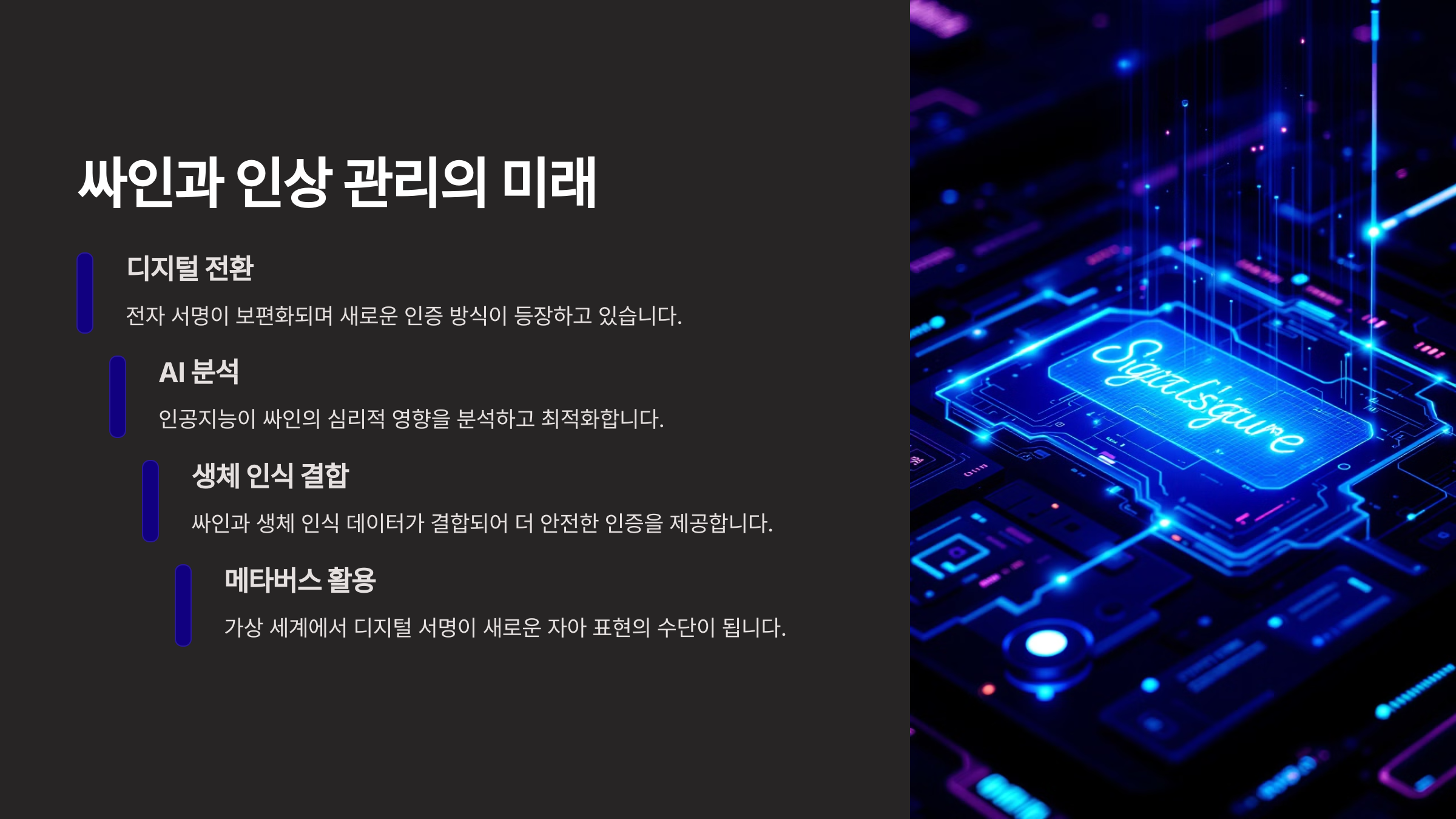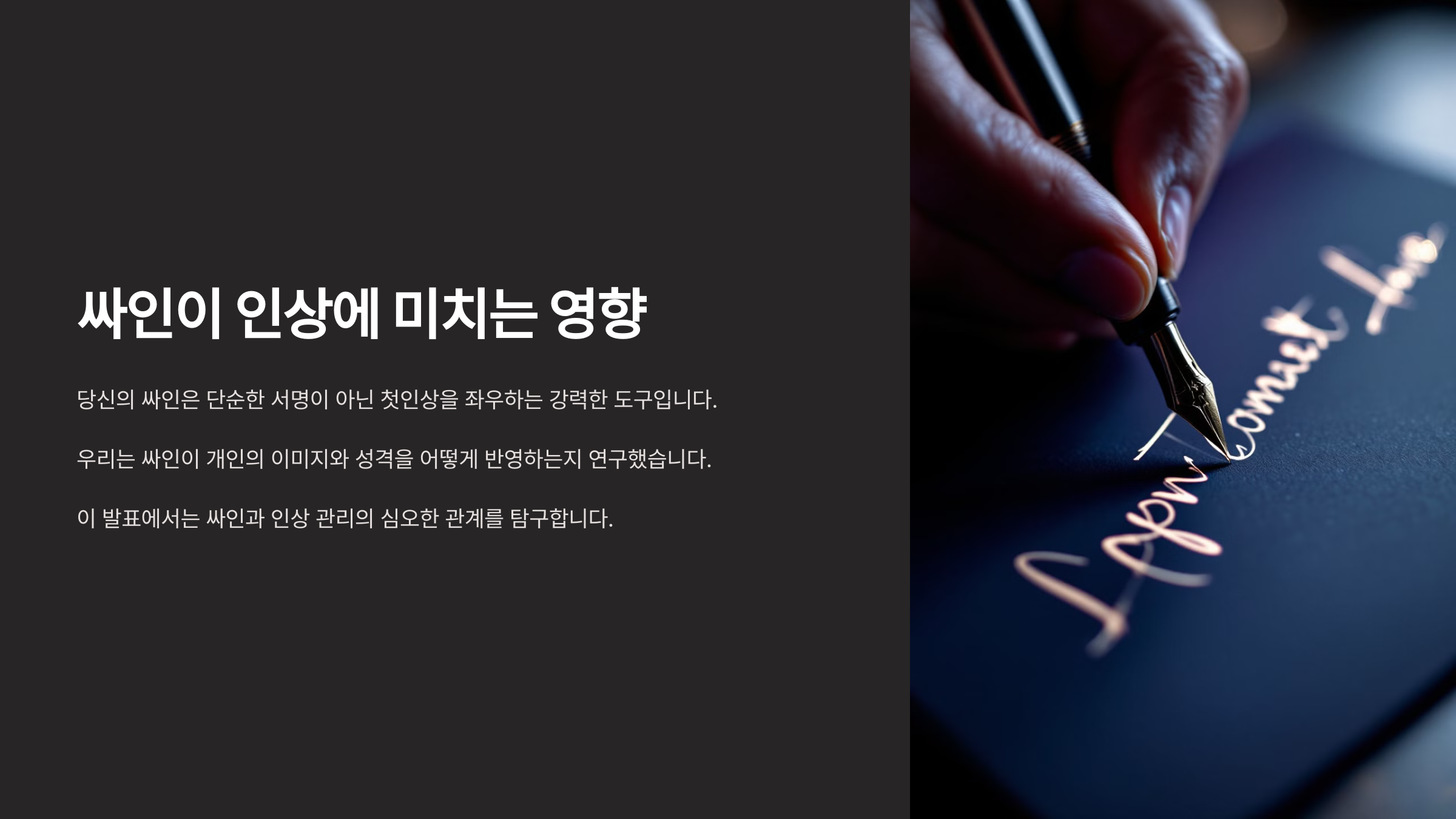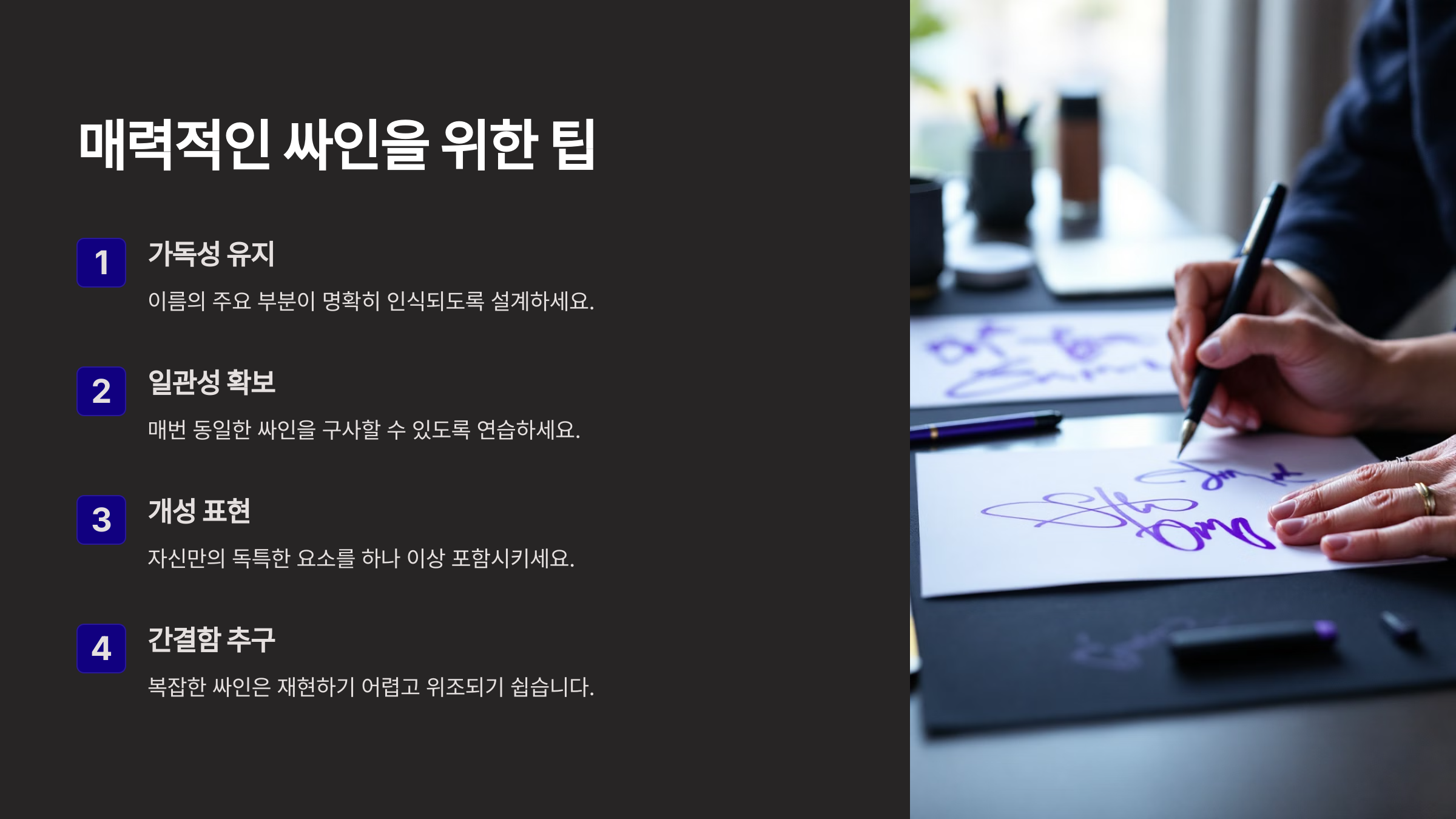
우리는 사람의 인상을 얼굴, 말투, 행동으로 판단하지만, 싸인 하나만으로도 인상이 달라 보일 수 있다는 사실! 알고 계셨나요? 🤔 싸인은 단순한 서명이 아니라 개성과 성향을 담은 또 하나의 얼굴이에요.
그럼 싸인을 바꾸면 어떤 인상 변화가 일어나는지 함께 알아볼까요? 🚀
싸인이 인상에 미치는 영향 👀
싸인은 우리가 의식하지 못하는 사이에 상대방에게 첫인상을 결정짓는 중요한 요소로 작용할 수 있어요. 그렇다면 싸인은 왜 사람의 인상에 영향을 미칠까요? 🤔
📌 싸인이 인상을 좌우하는 3가지 이유
• ✍ 필체의 감정 전달 → 싸인의 필체는 사람의 성향과 감정을 반영해요.
• 🔍 스타일의 상징성 → 싸인의 디자인이 곧 그 사람의 성격을 표현할 수 있어요.
• 💼 전문성과 신뢰감 → 세련된 싸인은 더 신뢰감을 주는 효과가 있어요.
싸인의 모양과 스타일이 달라지면 상대방이 느끼는 이미지도 달라질 수 있어요. 그럼 싸인의 심리학적 의미도 함께 살펴볼까요? 😆
싸인의 심리학적 의미 🧠
싸인은 단순한 글씨가 아니라 개성과 심리를 반영하는 요소예요. 어떤 스타일의 싸인을 사용하는지에 따라 그 사람의 성향과 성격이 드러날 수 있죠. 그렇다면 싸인의 형태별로 어떤 심리적 의미를 담고 있는지 살펴볼까요? 🤔
📌 싸인 스타일별 심리적 의미
싸인 스타일 심리적 의미
크고 화려한 싸인 자신감이 높고 외향적인 성격
작고 단순한 싸인 신중하고 내성적인 성격
곡선이 많은 싸인 감성적이고 창의적인 성향
직선 위주의 싸인 논리적이고 강한 리더십
기울어진 싸인 역동적이고 에너지가 넘치는 성격
이처럼 싸인의 디자인만 보고도 어느 정도 성향을 유추할 수 있어요. 그럼 싸인의 스타일별로 인상이 어떻게 변하는지도 알아볼까요? 🔍
싸인 스타일별 인상 변화 🔄
싸인의 스타일을 바꾸면 상대방이 받는 인상이 달라질 수 있어요. 같은 이름이라도 어떤 디자인을 적용하느냐에 따라 다른 분위기를 연출할 수 있죠! 그럼 스타일별 인상 변화를 비교해볼까요? 😊
📌 싸인 스타일에 따른 인상 변화
싸인 스타일 주는 인상
날렵한 필기체 싸인 스타일리시하고 세련된 느낌
굵은 획의 강한 싸인 신뢰감과 강한 카리스마
곡선이 많은 싸인 부드럽고 친근한 이미지
작고 정돈된 싸인 섬세하고 꼼꼼한 느낌
대각선으로 기울어진 싸인 역동적이고 활동적인 성격
싸인을 조금만 수정해도 전혀 다른 인상을 줄 수 있다는 것! 그럼 싸인을 바꾸기 전과 후의 차이를 비교해볼까요? 🤩
싸인 변경 전후 비교 🔄
싸인을 바꾸기 전과 후를 비교하면 상대방이 느끼는 인상이 어떻게 변하는지 명확히 알 수 있어요. 싸인을 조금만 수정해도 더 전문적이고 세련된 분위기를 연출할 수 있답니다! 🤩
📌 싸인 변경 전후 비교 사례
변경 전 변경 후 인상 변화
작고 삐뚤어진 싸인 균형 잡힌 필기체 싸인 더 정돈되고 신뢰감 있는 인상
단순한 이니셜 싸인 곡선과 기호가 추가된 싸인 더 개성 있고 창의적인 느낌
너무 복잡한 싸인 간결하고 깔끔한 디자인 더 세련되고 전문적인 이미지
기울어진 싸인 수평으로 정돈된 싸인 차분하고 안정적인 인상
획이 얇고 불안정한 싸인 굵은 획으로 강조된 싸인 강한 카리스마와 자신감 표현
이처럼 작은 변화만으로도 싸인의 분위기가 완전히 달라질 수 있어요. 그럼 더 매력적인 싸인을 만들기 위한 꿀팁도 함께 알아볼까요? 😉
매력적인 싸인을 위한 팁 ✨
싸인을 더 멋지게 만들고 싶다면, 다음 3가지 포인트를 기억하세요! 😊
🔹 더 매력적인 싸인을 만드는 3가지 팁
• ✔ 균형을 맞춘다 → 글자 크기와 간격을 일정하게 유지하세요.
• ✔ 자신만의 기호를 추가한다 → 별(⭐), 밑줄(__), 점(•) 등으로 개성을 살려보세요.
• ✔ 너무 복잡하지 않게 → 심플하면서도 개성 있는 디자인이 더 인상적이에요.
이제 매력적인 싸인을 위한 기본 원칙을 알았으니, 유명인들의 싸인 변화를 살펴보며 더 많은 인사이트를 얻어볼까요? 🔍
유명인의 싸인 변화 사례 🌟
많은 유명인들이 자신의 이미지를 더 강렬하게 만들기 위해 싸인을 바꾸거나 디자인을 수정하는 경우가 많아요! ✍ 그럼 유명인들의 싸인 변화를 살펴보면서 어떤 스타일이 효과적인지 알아볼까요? 🤩
📌 유명인의 싸인 변화 비교
유명인 초기 싸인 변경 후 싸인 인상 변화
스티브 잡스 단순한 필기체 더 직선적이고 간결한 스타일 더 미니멀하고 현대적인 느낌
마이클 잭슨 기본적인 이니셜 서명 곡선이 많고 화려한 스타일 예술적이고 감성적인 분위기
일론 머스크 작고 정돈된 싸인 더 크고 강한 필체 자신감 있고 강한 리더십 표현
도널드 트럼프 일반적인 필기체 싸인 뾰족하고 강렬한 직선 싸인 권위적이고 강한 인상
이처럼 싸인을 바꾸는 것만으로도 전혀 다른 인상을 줄 수 있어요! 그럼 마지막으로 싸인과 관련된 궁금한 점을 FAQ에서 해결해볼까요? ❓
FAQ ❓
Q1. 싸인을 바꾸면 정말 인상이 달라 보이나요?
A1. 네! 싸인은 개성을 나타내는 중요한 요소이기 때문에, 스타일이 바뀌면 상대방이 받는 느낌도 달라질 수 있어요. 예를 들어, 곡선이 많으면 부드럽고 친근한 인상, 직선이 많으면 강하고 신뢰감 있는 이미지를 줄 수 있어요. 😊
Q2. 싸인을 더 세련되게 바꾸는 가장 쉬운 방법은?
A2. 싸인을 더 세련되게 만들고 싶다면 다음 3가지를 기억하세요! ✔ 균형 잡힌 글자 크기 → 지나치게 크거나 작은 글자는 피하세요. ✔ 자연스러운 흐름 → 글자 간 연결이 매끄러우면 멋진 싸인이 돼요. ✔ 한 가지 포인트 추가 → 별(⭐), 밑줄(__), 점(•) 같은 기호를 활용하면 더 스타일리시해 보여요! ✨
Q3. 싸인의 크기가 클수록 더 좋은 인상을 줄까요?
A3. 꼭 그런 것은 아니에요. 큰 싸인은 자신감 있는 느낌을 주지만, 너무 크면 가독성이 떨어질 수도 있어요. 자신의 스타일에 맞게 적당한 크기로 조절하는 것이 가장 중요해요. 😉
Q4. 싸인을 바꿨는데 사람들이 이상하다고 하면 어떻게 하죠?
A4. 싸인은 개인적인 스타일이 반영된 요소이기 때문에 다른 사람들의 의견보다는 내가 만족할 수 있는 디자인을 찾는 것이 중요해요! 만약 너무 어색하다면 조금씩 수정하면서 자연스럽게 익숙해지는 과정이 필요할 수도 있어요. ✍
Q5. 싸인을 여러 번 바꾸는 것은 좋지 않은가요?
A5. 싸인을 자주 바꾸면 공식적인 서류에서 혼동이 생길 수 있어요. 그래서 자주 쓰는 싸인은 일관성을 유지하는 것이 가장 좋아요. 하지만 개인적인 싸인은 필요에 따라 변경해도 괜찮아요! 😆
Q6. 싸인을 연습하면 필체도 좋아질까요?
A6. 네! 싸인을 연습하면 손글씨의 흐름이 자연스러워지고, 더욱 균형 잡힌 필체를 만들 수 있어요. 정확한 획과 부드러운 곡선을 연습하면 전체적인 필기 실력도 향상될 수 있답니다! 📝
Q7. 싸인 디자인에 법적인 제한이 있을까요?
A7. 싸인은 본인이 직접 작성한 것이라면 법적으로 문제되지 않아요. 다만, 공식적인 문서에서는 너무 복잡한 싸인보다는 간결한 싸인이 더 신뢰감을 줄 수 있어요. 😉
Q8. 유명인들의 싸인을 따라 해도 될까요?
A8. 참고는 가능하지만, 그들의 싸인을 그대로 사용하는 것은 추천하지 않아요. 싸인은 본인의 개성을 반영하는 것이 중요하기 때문에, 참고하면서 나만의 스타일을 만들어가는 것이 가장 좋아요! 😍
싸인은 작은 변화만으로도 완전히 다른 인상을 줄 수 있는 강력한 요소예요. 더욱 세련되고 자신감 있는 싸인을 원한다면, 📌 균형감 있는 디자인 📌 자연스러운 필체 📌 나만의 개성을 담은 포인트 이 세 가지를 꼭 기억하면서 싸인을 디자인해보세요! 🚀